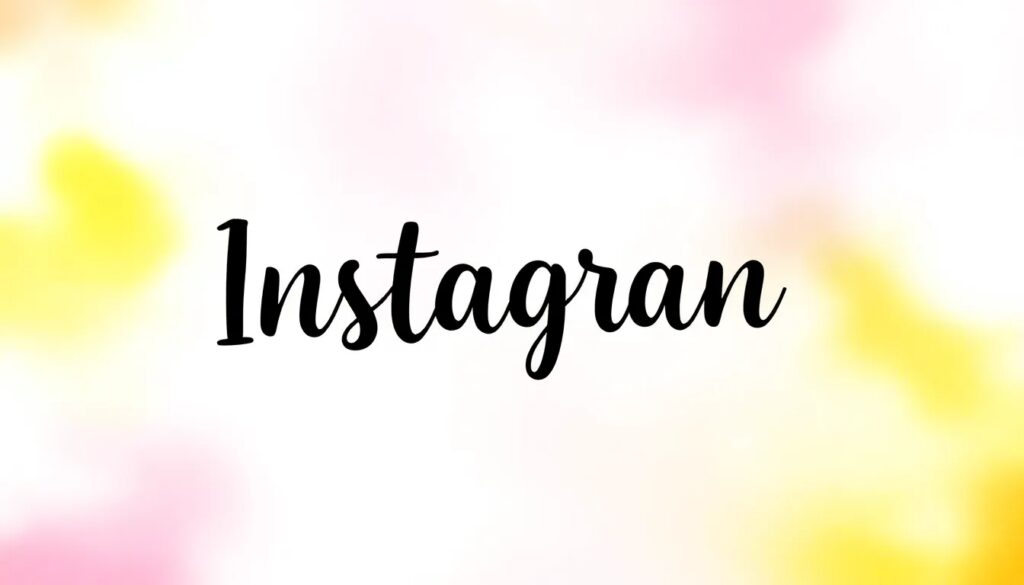
Font for Instagram: generador de estilos y letras
Las redes sociales han transformado la manera en que nos comunicamos y expresamos nuestra personalidad. En este contexto, las fuentes para Instagram han cobrado gran relevancia, permitiendo a los usuarios personalizar sus perfiles de forma atractiva. En este artículo, exploraremos cómo un generador de fuentes puede ayudarte a destacar en esta plataforma.
Utilizar un font for instagram no solo embellece tus publicaciones, sino que también invita a tus seguidores a interactuar con tu contenido. A continuación, responderemos a las preguntas más frecuentes sobre este tema y te mostraremos cómo sacarle el máximo provecho a estas herramientas.
¿Qué son las fuentes para Instagram?
Las fuentes para Instagram son estilos de texto que se utilizan para personalizar publicaciones y biografías. A menudo, estos estilos no son fuentes en el sentido tradicional, sino que se construyen a partir de caracteres Unicode que simulan diferentes tipos de escritura.
La idea es ofrecer a los usuarios la posibilidad de utilizar letras únicas para publicaciones en Instagram, que llamen la atención y se diferencien del texto estándar. Esto se traduce en un perfil más atractivo y dinámico.
Estas fuentes pueden incluir estilos como cursivas, negritas y diversos símbolos decorativos, los cuales añaden un toque distintivo a tu contenido. Además, son fáciles de implementar y no requieren conocimientos técnicos.
¿Cómo funciona un generador de fuentes para Instagram?
Un generador de fuentes para Instagram es una herramienta en línea que permite a los usuarios crear textos estilizados. Simplemente, se ingresa el texto original y la herramienta genera diferentes estilos que se pueden copiar y pegar en Instagram.
El proceso es ágil y no requiere descargas. Además, puedes ver los resultados instantáneamente, lo que facilita la elección del estilo que más te guste. Muchos de estos generadores son gratuitos y accesibles desde cualquier dispositivo.
- Ingresa el texto que deseas estilizar.
- Selecciona el estilo que más te guste.
- Copiar el texto estilizado y pegarlo en tu publicación o biografía.
Así de sencillo es crear fuentes decorativas para Instagram que resalten tu perfil y lo hagan más memorable.
¿Cuáles son los estilos de fuentes más populares para Instagram?
Existen múltiples estilos de fuentes que puedes utilizar para personalizar tu perfil. Algunos de los más populares incluyen:
- Cursiva: Ideal para dar un toque elegante.
- Negrita: Perfecta para resaltar información importante.
- Textos decorativos: Incluyen símbolos y caracteres especiales que añaden originalidad.
- Minúsculas estilizadas: Para un enfoque más informal y amigable.
Cada uno de estos estilos tiene su propio impacto visual y puede ser utilizado según la ocasión. Ya sea para una biografía llamativa o para publicaciones que destaquen, las posibilidades son infinitas.
¿Cómo usar un generador de fuentes en Instagram?
Usar un generador de fuentes en Instagram es un proceso simple. Primero, elige un generador en línea y sigue estos pasos:
- Ingresa el texto que deseas estilizar.
- Explora los diferentes estilos que te ofrece el generador.
- Copia el texto estilizado.
- Pega el texto en tu publicación o biografía de Instagram.
Este enfoque te permite experimentar y encontrar el estilo perfecto que refleje tu personalidad. No olvides combinar estos textos con emojis o imágenes para un efecto aún más atractivo.
¿Son las fuentes de Instagram realmente fuentes?
Técnicamente, las fuentes que ves en Instagram no son fuentes en el sentido clásico. Se basan en caracteres Unicode que, aunque simulan diferentes estilos, no son tipografías auténticas que puedas descargar o utilizar fuera de esta plataforma.
Estos caracteres se visualizan de manera diferente según el dispositivo y la aplicación, lo que significa que la experiencia de quienes vean tu contenido puede variar. Sin embargo, esto no disminuye su atractivo: las fuentes personalizadas para biografía de Instagram son una excelente manera de destacar.
A pesar de no ser fuentes tradicionales, los estilos generados son una herramienta eficaz para realzar la personalidad de tu perfil y hacer que tus publicaciones se destaquen.
¿Cómo puedo copiar y pegar letras bonitas para Instagram?
Copiar y pegar letras estilizadas para Instagram es un proceso sencillo. Una vez que hayas generado el texto a través del generador de letras para redes sociales, simplemente sigue estos pasos:
- Selecciona el texto estilizado que deseas copiar.
- Haz clic derecho y selecciona "Copiar" o usa el atajo de teclado Ctrl+C (Cmd+C en Mac).
- Ve a Instagram y selecciona el área donde deseas pegar el texto.
- Haz clic derecho y selecciona "Pegar" o utiliza Ctrl+V (Cmd+V en Mac).
Este proceso te permite personalizar tu contenido de manera rápida y eficiente. Recuerda siempre previsualizar cómo se verá el texto en tu publicación antes de publicarlo.
En conclusión, el uso de un font for instagram puede transformar tu perfil y hacerlo más atractivo. Aprovecha la variedad de estilos y personaliza tus publicaciones para destacar en esta popular red social.